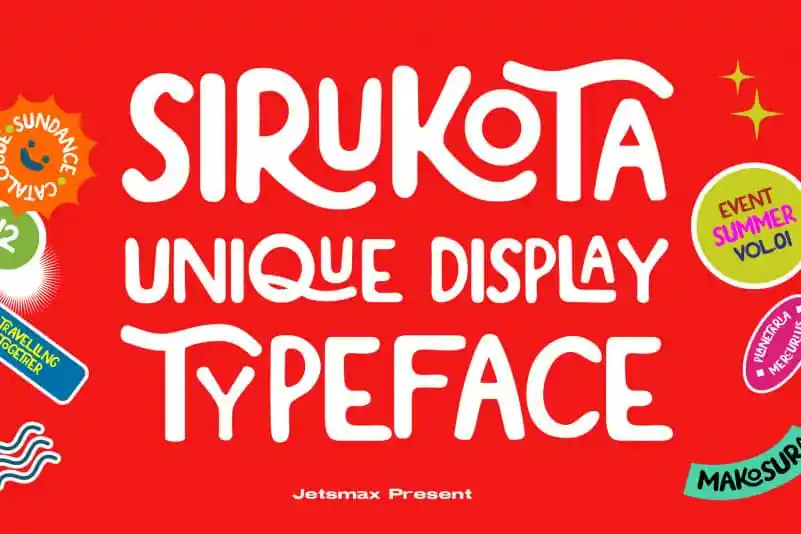
Sirukota Display Font – Fonte Grátis
Sirukota Display Font
A Sirukota Display Font é uma fonte de tipo com aparência vibrante e única, projetada para dar vida aos seus projetos digitais. Com os seus caracteres especiais, a Sirukota pode enriquecer qualquer layout, dando-lhe um toque especial que faz toda a diferença. Para designers ou criativos que buscam algo diferente e envolvente, esta fonte é uma escolha ótima para introduzir um toque único em projetos visuais. Não importa se for gráficos digitais, design de logotipos ou editoração de textos, a Sirukota Display Font trará uma sensação especial à sua obra. Com seu design moderno e versátil, essa fonte é perfeita para quem quer criar algo autêntico e impactante sem precisar investir muito tempo na criação.